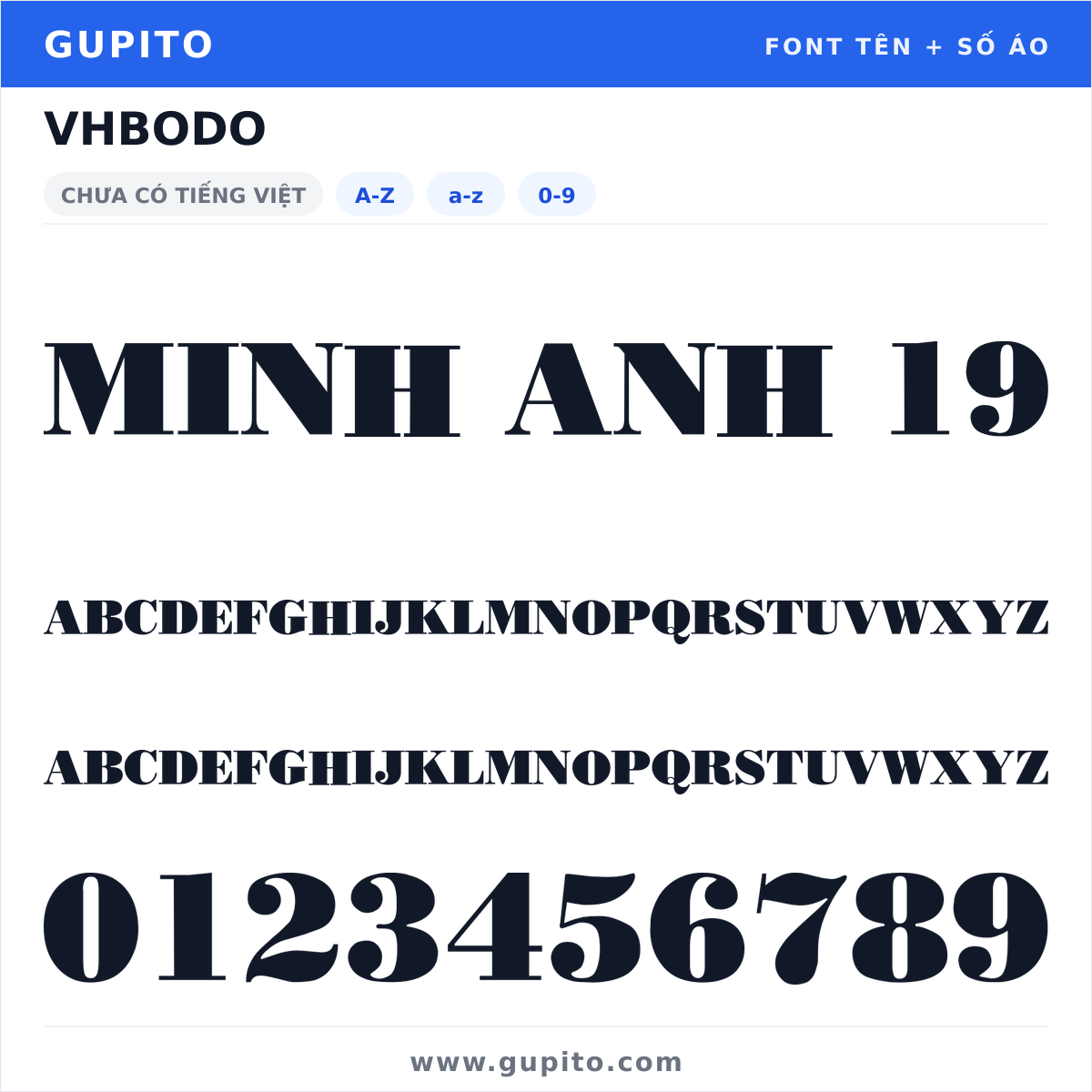
.VnBodoniH
.VnBodoniH · Font VHBODO in áo bóng đá, áo lớp, tên số · chữ đậm chân vuông
Font VHBODO với nét chữ đậm, chân chữ vuông vắn, phù hợp in tên áo bóng đá, áo lớp, áo đội, quà tặng. Có bảng số 0-9. Bộ chữ .VnBodoniH dùng để in chuyển nhiệt lên áo đấu, áo lớp, áo nhóm và đồ thể thao theo yêu cầu. Kiểu dáng: chữ đậm chân vuông. Font dùng cho chữ không dấu và số áo. Có đủ bộ chữ số để in số áo. Từ khoá liên quan: font vhbodo, font in ten ao, font in so ao, font ao bong da, font ao lop, font in chuyen nhiet, font co bang so, font chu hoa.